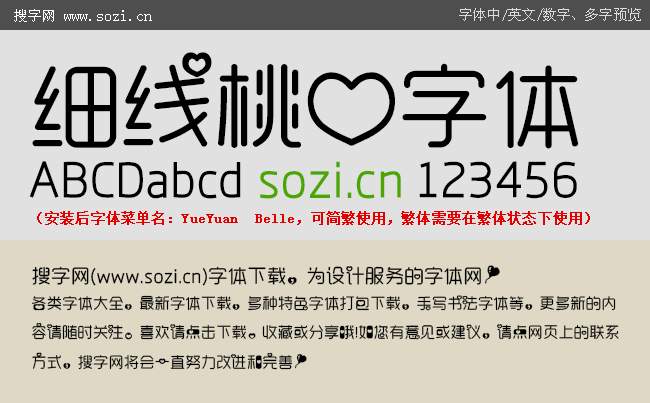
細(xì)線桃心字體
搜字網(wǎng)給大家提供一款很有趣的手機(jī)中文字體下載。字體名字叫細(xì)線桃心字體,這款手機(jī)字體是以造字工房悅黑體字體為原形,個別筆畫被替換成了卡通圖案,標(biāo)點(diǎn)符號也替換成了卡通圖案。即保持了悅黑體易識別的風(fēng)格,又增強(qiáng)了趣味性,特別適合喜歡手機(jī)字體個性一些的朋友在手機(jī)上安裝使用。